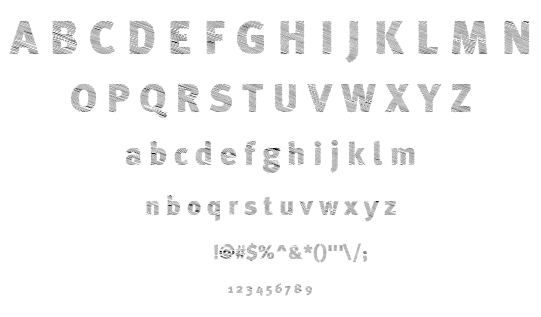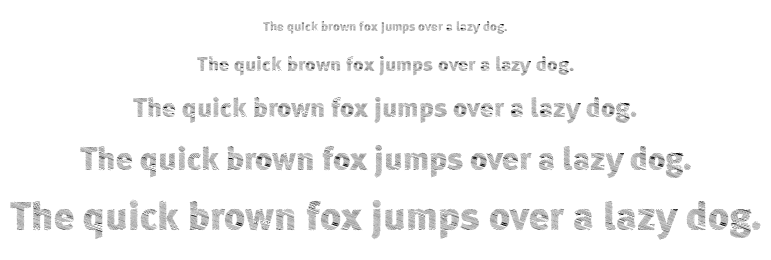
“A bebedera” – esta frase portuguesa viene a significar “la borrachera“, le he puesto el nombre a la tipografía por la cantidad de curvas que tiene cada glifo…(el vaiven del borracho, y el mareo que me he cogido haciéndola:), también como homenaje a Brasil, donde viví, disfruté y aprendí tanto.
Bueno, en realidad la idea del acabado garabateado de la fuente ha sido recrear un tipo de dibujos que suelo hacer a boli cuando hablo al teléfono… nu se, una manía!